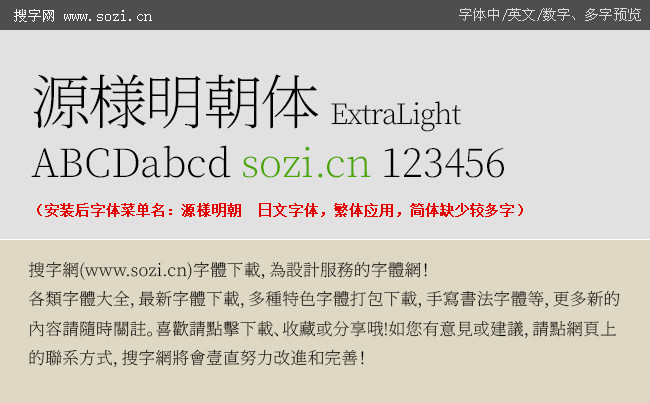
源様明朝ExtraLight
搜字網(wǎng)給大家提供一款源様明朝ExtraLight文字體下載,源様明朝體源自思源宋體,源樣明體采用思源宋體韓文版本的字符,配合繁體中文習(xí)慣的置中標(biāo)點(diǎn)符號(hào),可說是兼具排版及傳統(tǒng)印刷體風(fēng)格的繁體中文字體。適用于大標(biāo)題、包裝設(shè)計(jì)、海報(bào)設(shè)計(jì)等應(yīng)用。